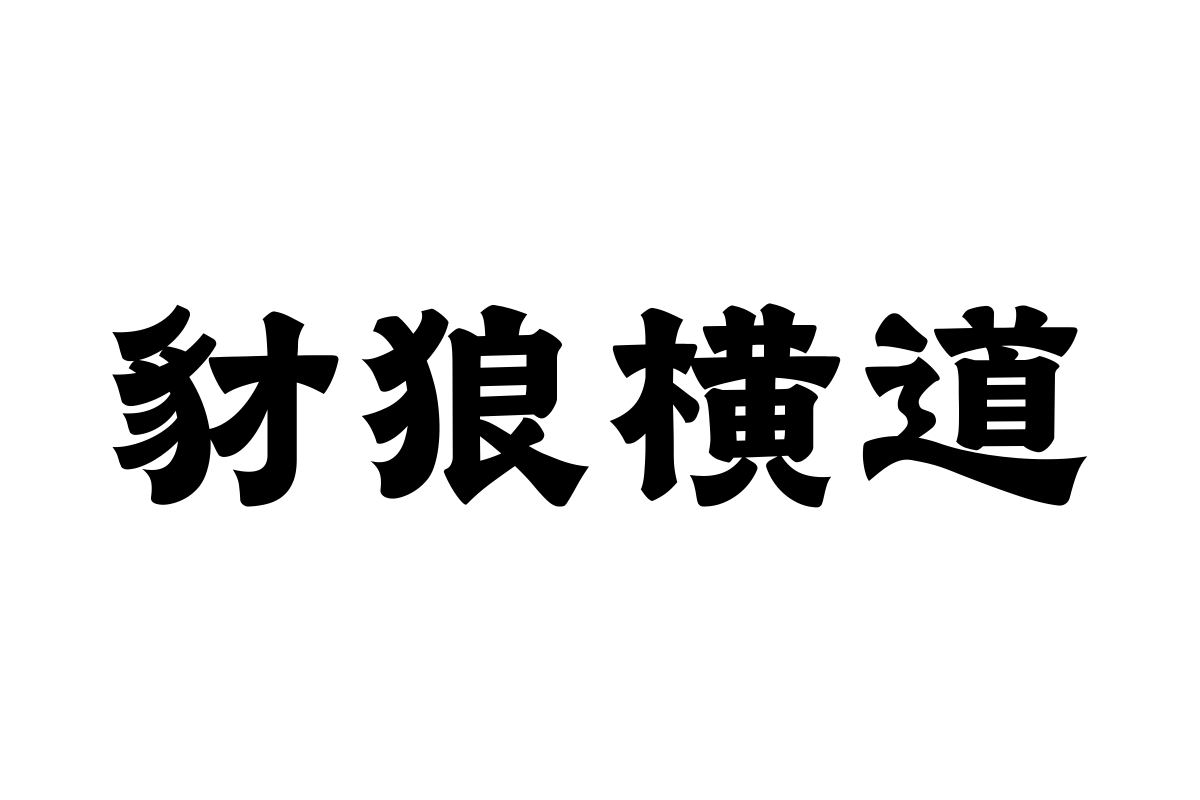
汉仪永字流云隶繁是一套由汉仪公司推出的书法字体,主要用于中文排版设计。这套字体的特点是笔画流畅,结构严谨,具有很高的艺术性和实用性。
汉仪永字流云隶繁采用了传统的隶书风格,但又在笔画上进行了创新和简化,使得整个字体更加现代和易于阅读。它的笔画粗细变化丰富,既有粗犷的线条,又有细腻的笔触,能够适应各种设计风格的需求。
此外,汉仪永字流云隶繁还具有一定的可读性,无论是用于标题、正文还是广告等场合,都能展现出良好的视觉效果。同时,它也能够很好地与各种字体搭配使用,提高整体的设计效果。
总之,汉仪永字流云隶繁是一款非常实用的中文字体,适合用于各类中文排版设计。